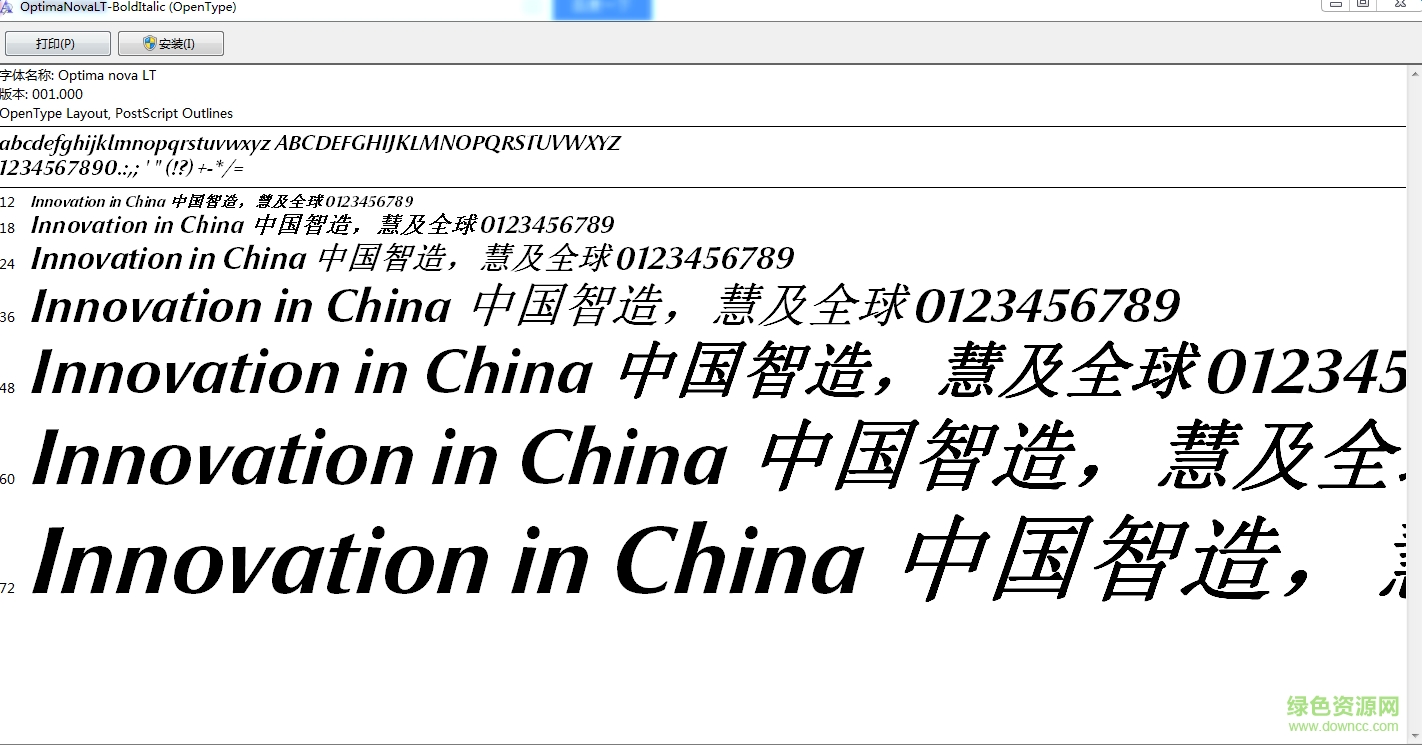
optima nova字體是一款英文斜體字體,字體筆畫精煉,構(gòu)思精巧,所有線條傾角度都非常一致,同時(shí)支持中英文和數(shù)字的輸入,可起到強(qiáng)調(diào)文字的效果!
在西文中斜體主要在以下場合使用:
1.表示強(qiáng)調(diào),喚起注意
2.書籍名稱、文章標(biāo)題、船舶名稱等
3.表示引用
4.外語,如英文文章中夾雜的法語(例:A splendid coq au vin was served. )
當(dāng)字體沒有斜體時(shí)可以考慮使用偽斜體代替。
打字機(jī)、手寫等無法使用斜體的時(shí)候遇到上述情況使用下劃線或引號(hào)加以區(qū)別;另外,當(dāng)斜體中又遇到上述情況時(shí),使用正體加以區(qū)別。